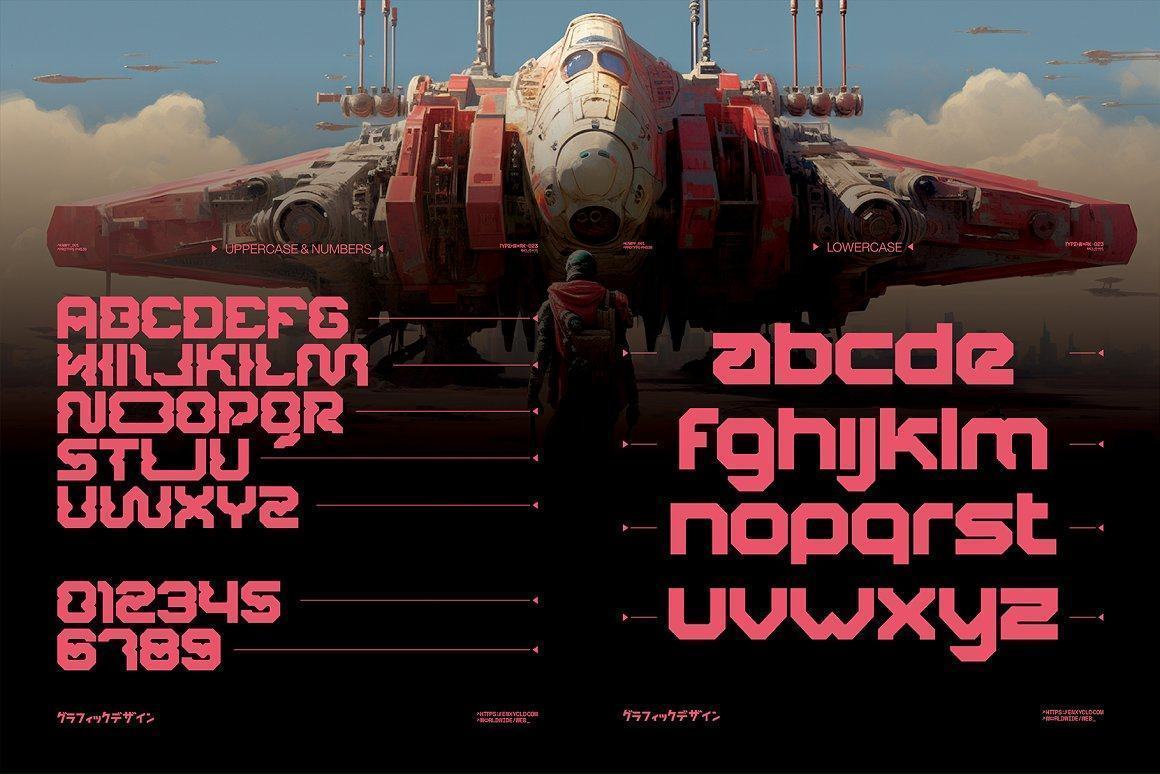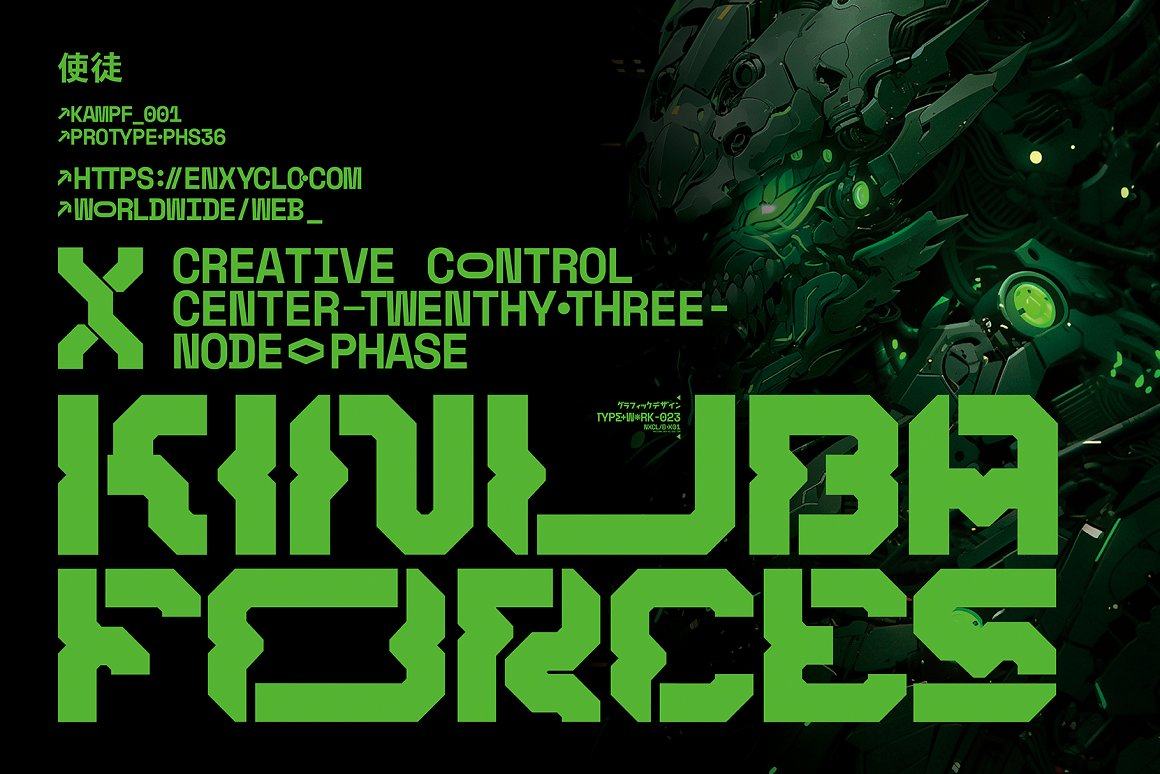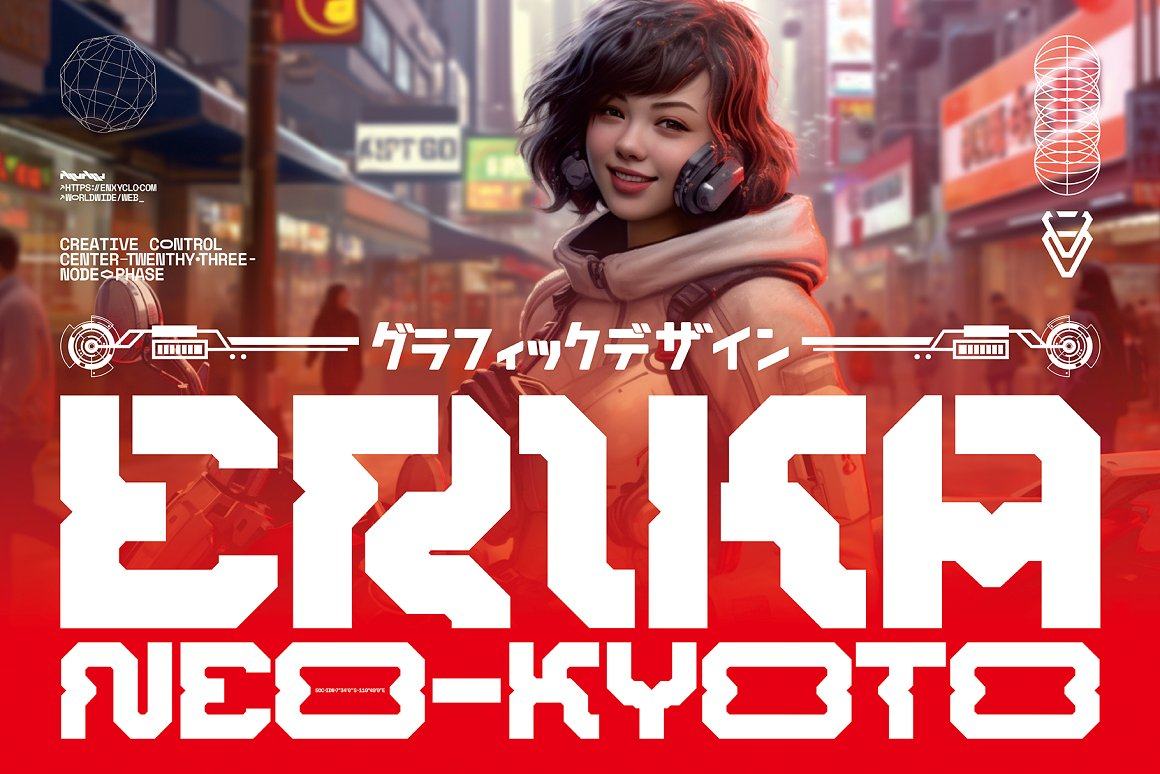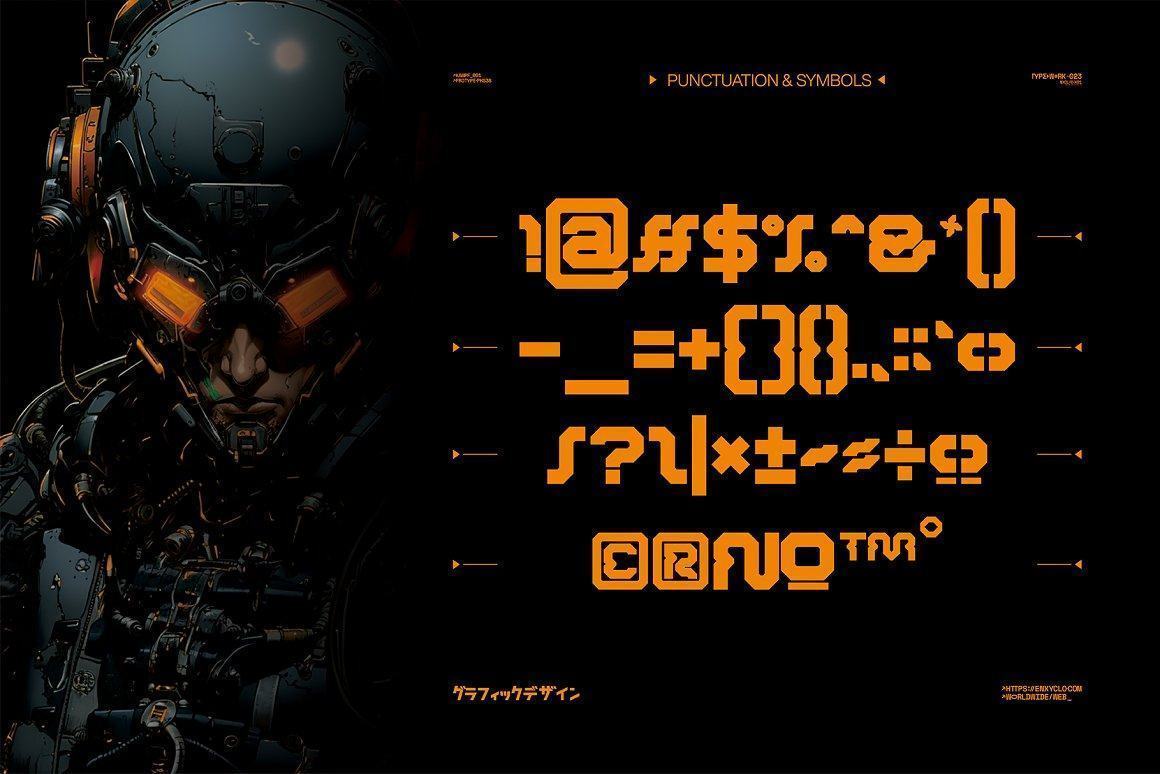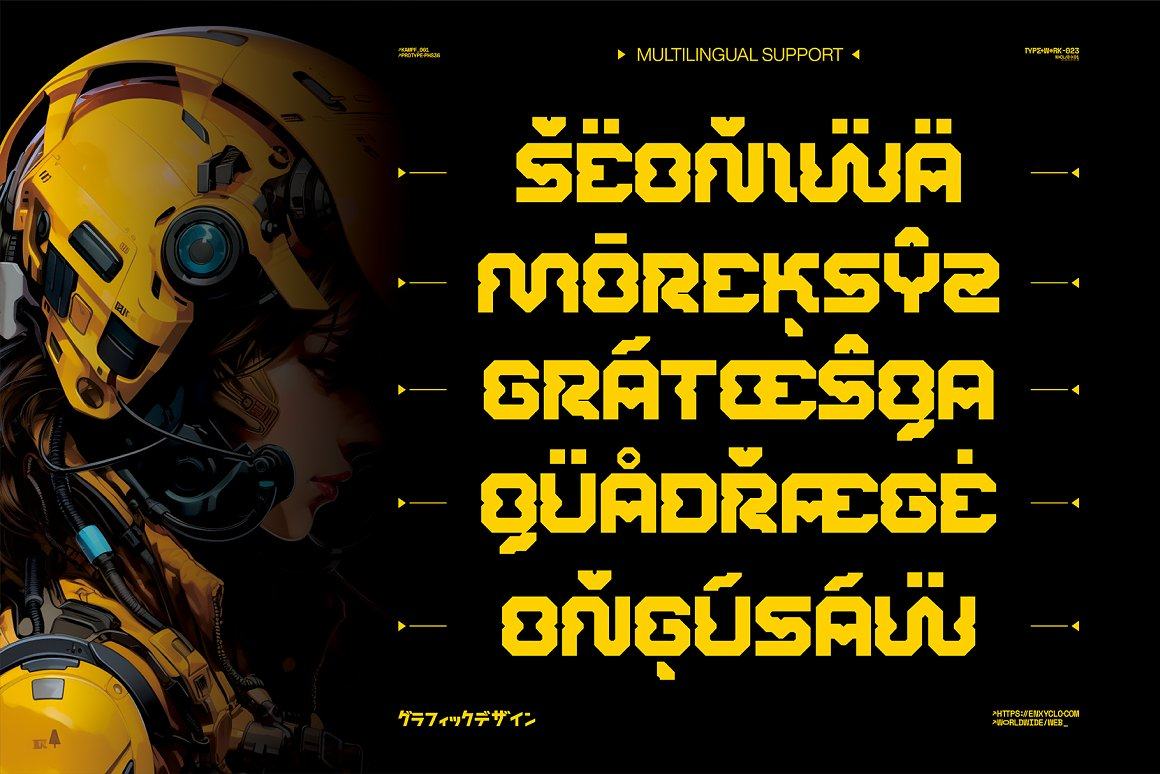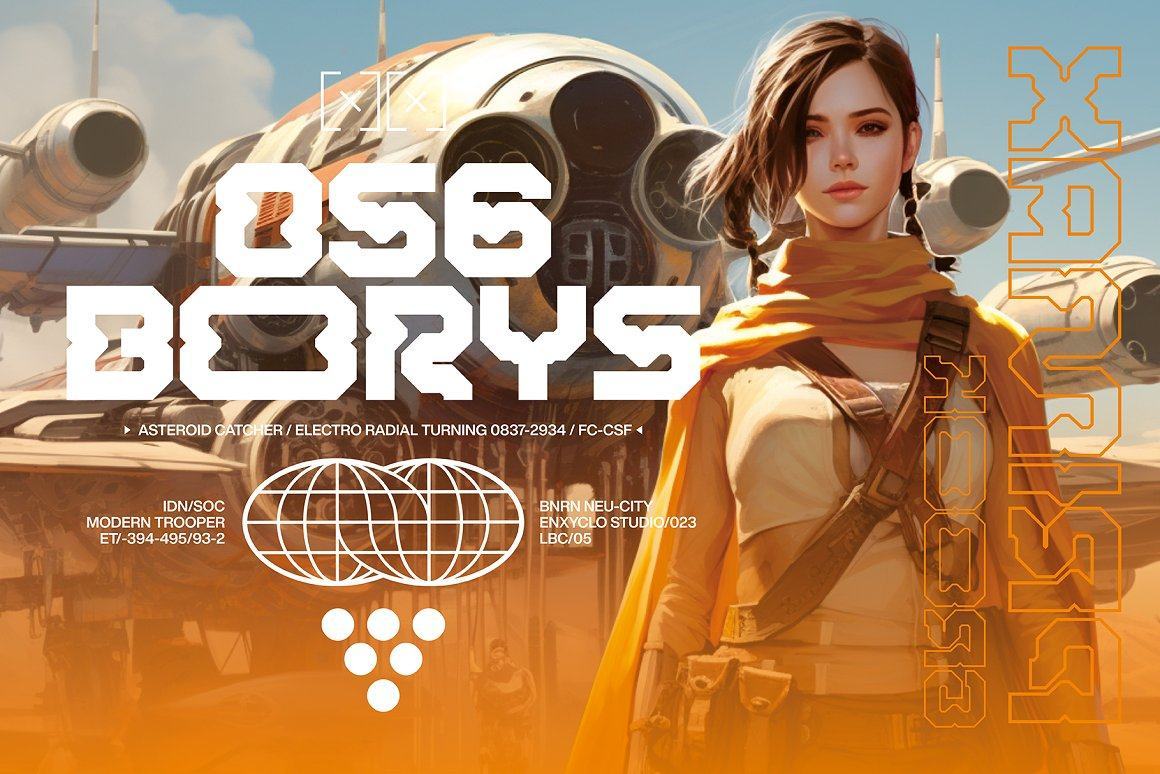
NCL ROBOWAPIX – Cyberpunk Futuristic Font
NCL ROBOWAPIX không phải là phông chữ thông thường của bạn; đó là phông chữ techno mecha tương lai của cyberpunk với 8 kiểu (Thông thường, Nghiêng thường xuyên, Phác thảo thường xuyên, Nghiêng phác thảo thông thường, Mecha, Mecha Slanted, Mecha Outline, Mecha Outline Slanted) đưa khả năng sáng tạo của bạn lên một tầm cao mới. Tính thẩm mỹ tương lai của nó mang đến một chiều hướng hoàn toàn mới cho các thiết kế của bạn, khiến chúng trở nên nổi bật. Cho dù bạn đang làm việc trên một trang web, áp phích, logo hay bất kỳ dự án nào khác, phông chữ này sẽ bổ sung thêm cảm giác đổi mới và tinh tế.
Cyberpunk–một thể loại bắt đầu từ khoa học viễn tưởng và đã để lại dấu ấn khó phai mờ trên nhiều khía cạnh khác nhau của văn hóa đại chúng, bao gồm cả thiết kế. Khó có thể bỏ qua kết cấu của Cyberpunk. Sức hấp dẫn nội tại của nó nằm ở sự pha trộn nghịch lý giữa cái tiên tiến và cái lỗi thời, cái tươi sáng và sự trầm tư, cái hy vọng và cái tuyệt vọng. Và một cách để truyền tải cảm xúc này một cách mạnh mẽ là thông qua phông chữ này – nếu bạn muốn, đây sẽ là những anh hùng trong giao tiếp bằng hình ảnh.
Cho dù bạn là nhà thiết kế đồ họa đang làm việc trong một dự án tương lai, nhà làm phim tạo tiêu đề cho bộ sử thi khoa học viễn tưởng tiếp theo của bạn hay đơn giản là người hâm mộ thẩm mỹ Cyberpunk, phông chữ này sẽ đóng vai trò là người dẫn đường cho bạn, soi sáng con đường của bạn trên những con phố đầy bóng tối của ngôn ngữ thiết kế độc đáo này.
Việc sử dụng phông chữ tương lai tuyệt đẹp này sẽ khiến dự án của bạn trở thành một kiệt tác thu hút sự chú ý. Nó có thể ngay lập tức thu hút khán giả của bạn và để lại ấn tượng lâu dài. Đó là sự lựa chọn hoàn hảo cho những ai dám khác biệt và muốn thoát khỏi sự bình thường. Nếu bạn đang tự hỏi làm thế nào để sử dụng phông chữ này tốt nhất, hãy xem các bản xem trước. Họ sẽ mang đến cho bạn nguồn cảm hứng đáng kinh ngạc để kết hợp phông chữ này vào thiết kế của bạn. Từ trang web đẹp mắt và hiện đại đến những áp phích bắt mắt, khả năng là vô tận.
Được thiết kế tuyệt vời để trở thành phông chữ được yêu thích thực sự, phông chữ này có khả năng đưa từng ý tưởng sáng tạo của bạn lên mức cao nhất! Nó được thiết kế có mục đích để sử dụng ở kích thước điểm lớn, mặc dù nó không mất đi tính kỳ diệu ở kích thước điểm nhỏ. Phông chữ này sẽ là một tài sản đáng kinh ngạc cho thư viện phông chữ của bạn, vì nó có khả năng nâng tầm mọi sáng tạo. Với phông chữ đẹp này, bạn hoàn toàn có thể làm cho dự án của mình nổi bật so với phần còn lại. Hãy để trí tưởng tượng của bạn được phát huy khi bạn hình dung ra tác động mà kiểu chữ tuyệt vời này có thể mang lại cho dự án của bạn.
ĐẶC TRƯNG
• 8 kiểu: Đều đặn, nghiêng đều, phác thảo thường nghiêng, Mecha, Mecha nghiêng, phác thảo Mecha, phác thảo Mecha nghiêng
• Chứa 256 Glyph cho mỗi kiểu và 2048 Glyph cho tổng số
• Chữ in hoa chữ thường
• Chữ số, dấu câu và ký hiệu